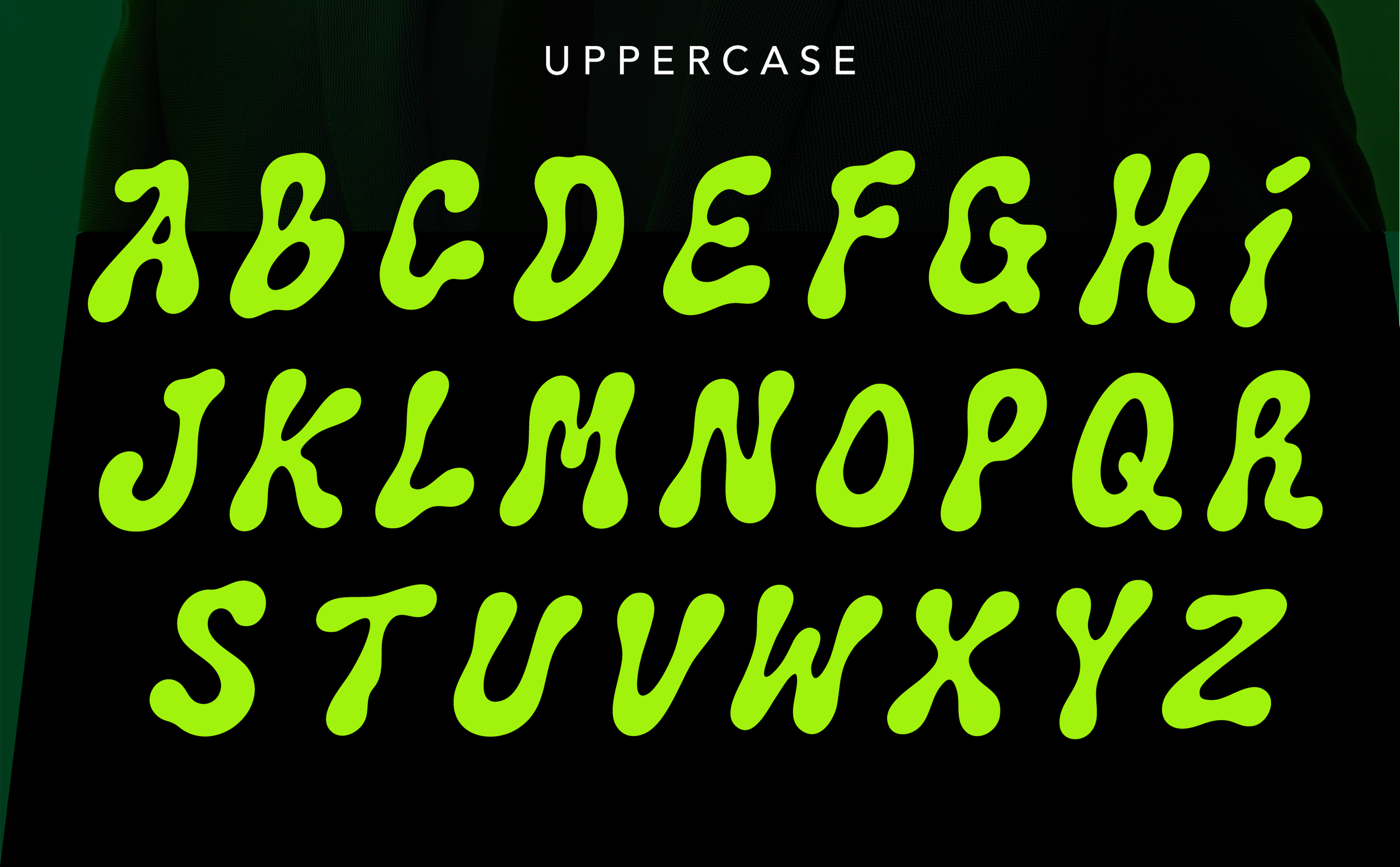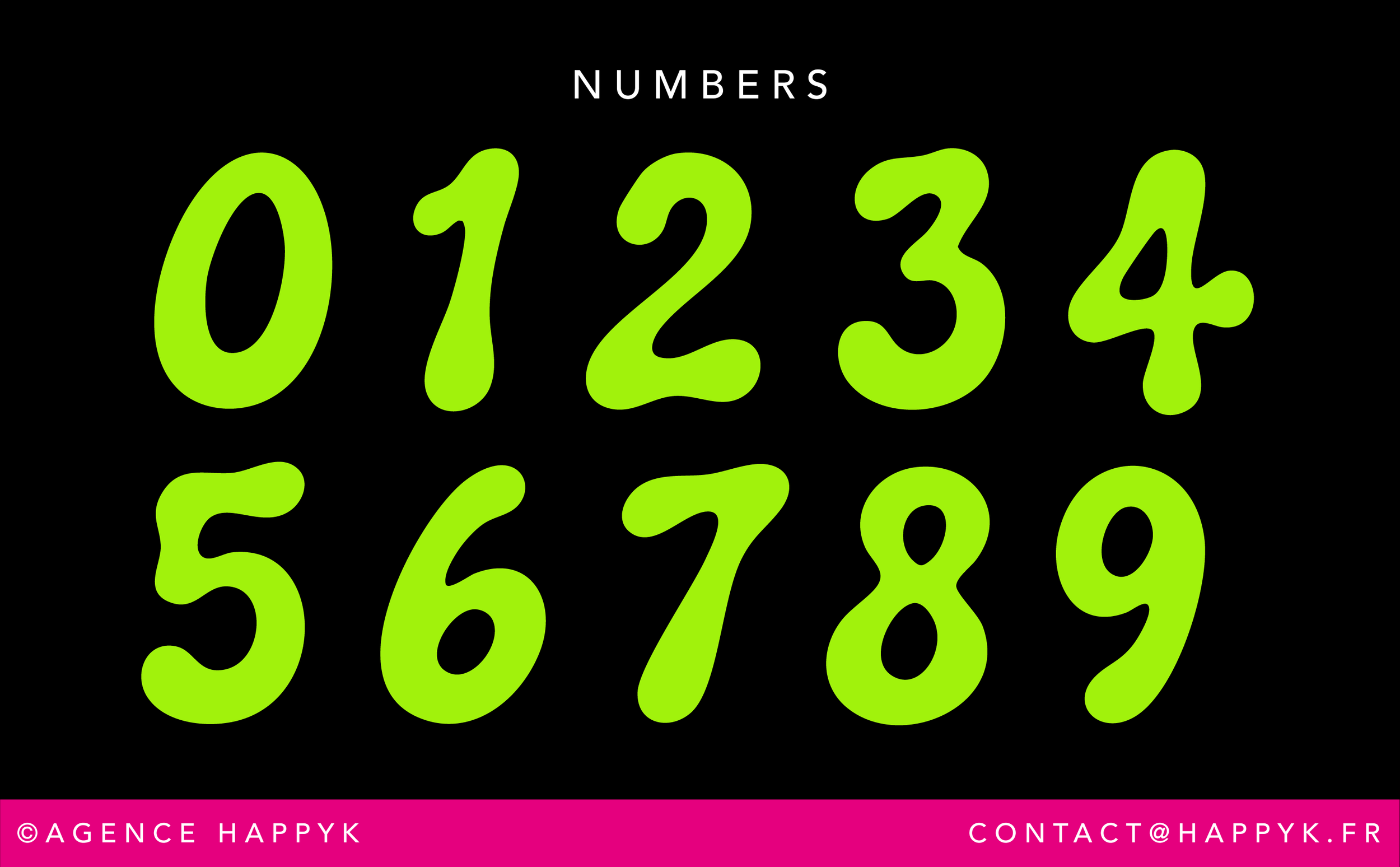
WEIRDO
La police qui a échappé au laboratoire.
WEIRDO est une typographie organique, visqueuse et délicieusement étrange. Inspirée des créatures mutantes, des films de science-fiction et des bonbons radioactifs, elle transforme chaque mot en une matière vivante.
Ses formes irrégulières et dégoulinantes lui donnent une personnalité unique, parfaite pour les affiches, les univers fantastiques, l’horreur fun, les jeux vidéo, les événements ou les marques qui refusent d’être ordinaires.
Bizarre, assumée et impossible à ignorer, WEIRDO est faite pour les projets qui aiment sortir du cadre.